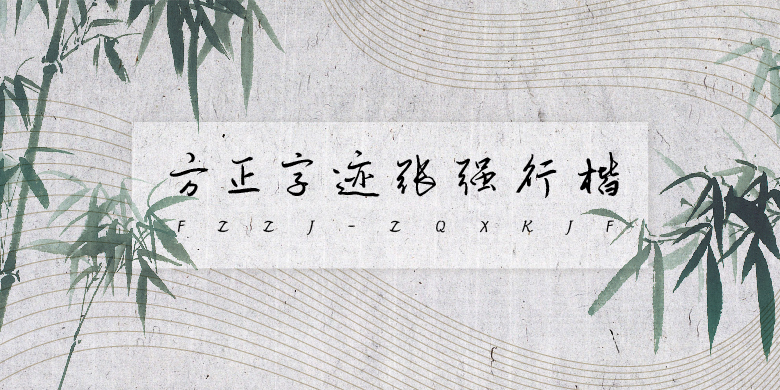
方正字迹-张强行楷
方正字迹-张强行楷,这款字体结构工整、笔画清晰,兼顾美观与易读性,适用于标题、正文、海报、包装、LOGO 等多种场景。字形优雅稳定,风格百搭耐看,适配日常排版与创意设计,让文字呈现更舒适、更具质感。方正字迹-张强行楷一笔一画,皆是细节,以均衡的比例、流畅的线条打造舒适视觉体验,字形端正大气,风格简约现代。无论是商业设计、品牌宣传还是日常排版,都能轻松驾驭,让文字更有格调与力量。方正字迹-张强行楷字体下载。
该款字结合了传统毛笔软笔和现代硬笔的写法和特点,使其既有毛笔的圆润厚重,又有现代硬笔的骨感和洒脱,线条比硬笔粗,比毛笔细,保留了传统的元素,同时又规避了纯硬笔的杂乱,这样不会显得太呆板。